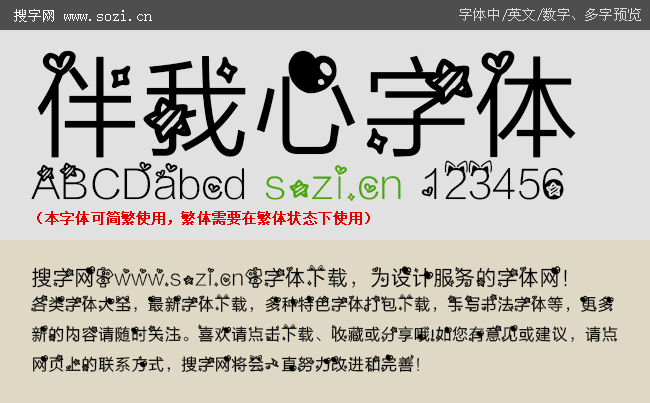
伴我心字體
搜字網(wǎng)給大家提供一款有趣的手機(jī)中文字體下載。修改者給它起名為伴我心字體,這款手機(jī)中文字體以黑體為原形,字體間點(diǎn)綴了很多可愛的星星與愛心等卡通圖形,即保持了黑體端正,易認(rèn)的特點(diǎn),又增添了趣味性,非常適合喜歡個性的朋友在手機(jī)上安裝使用。